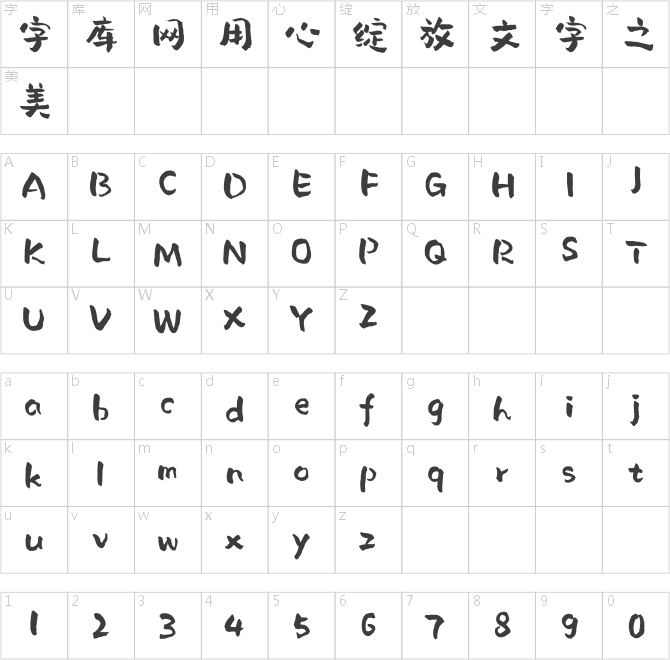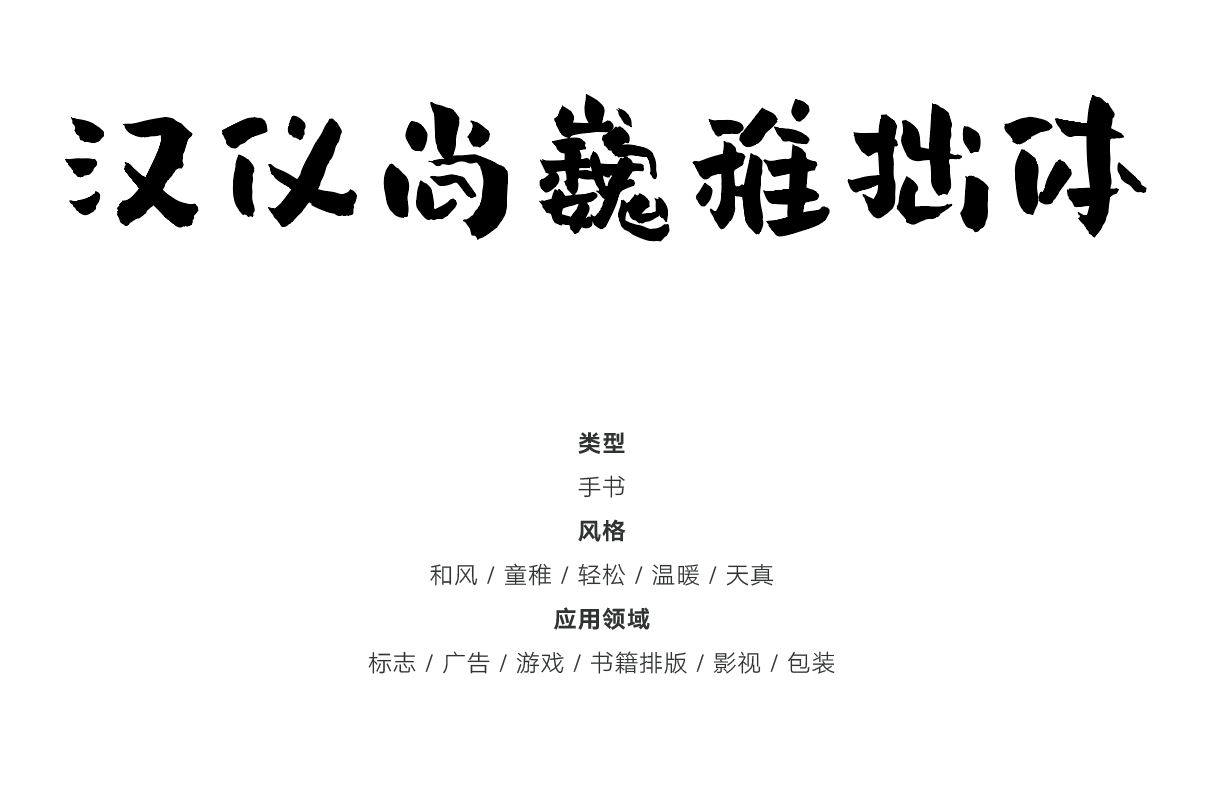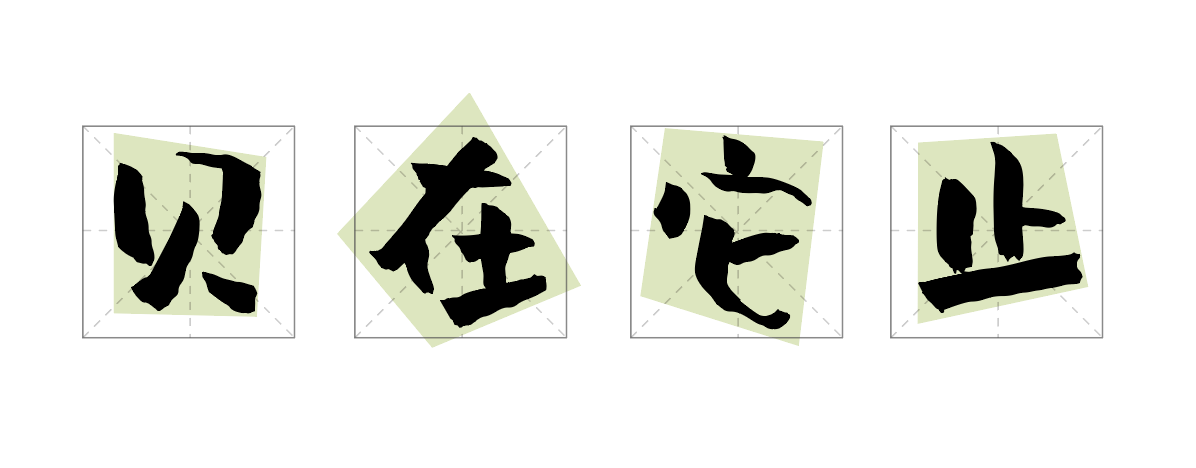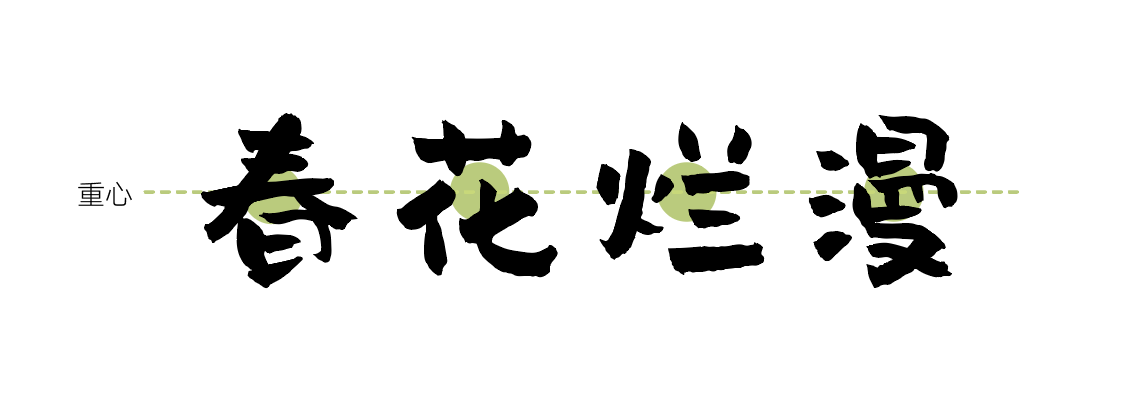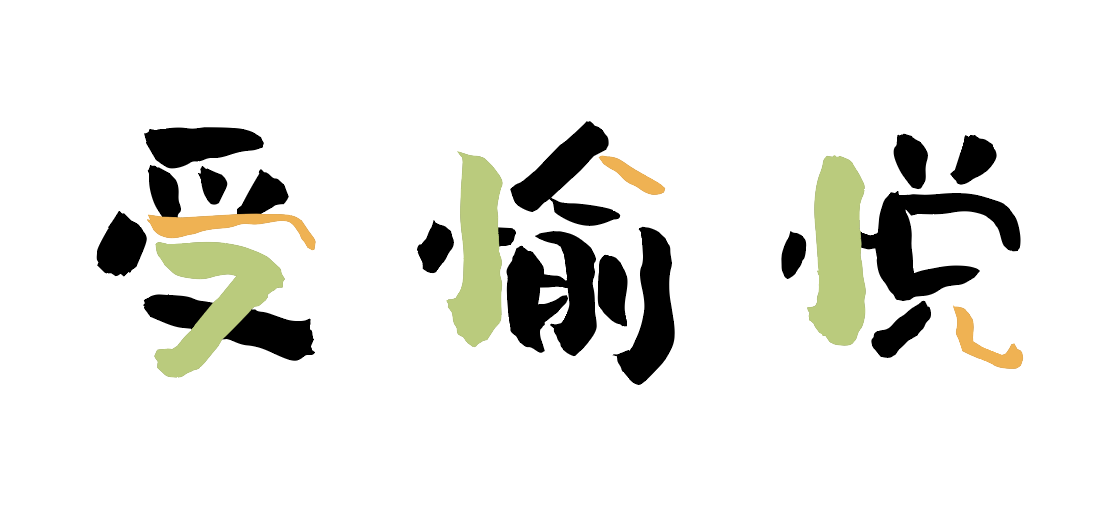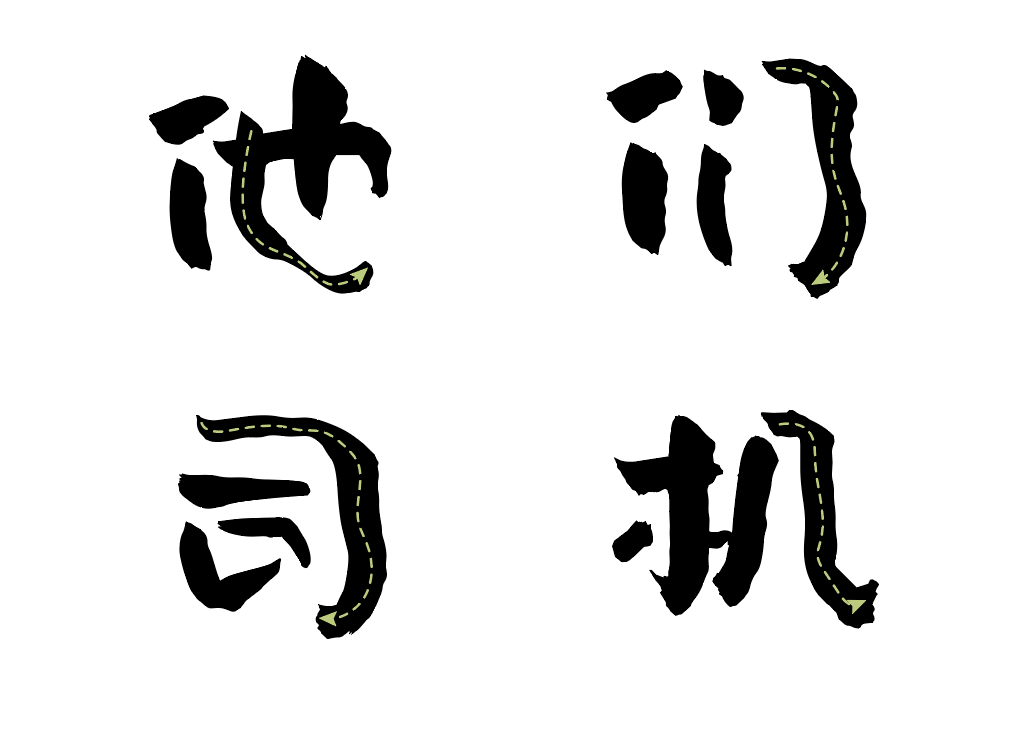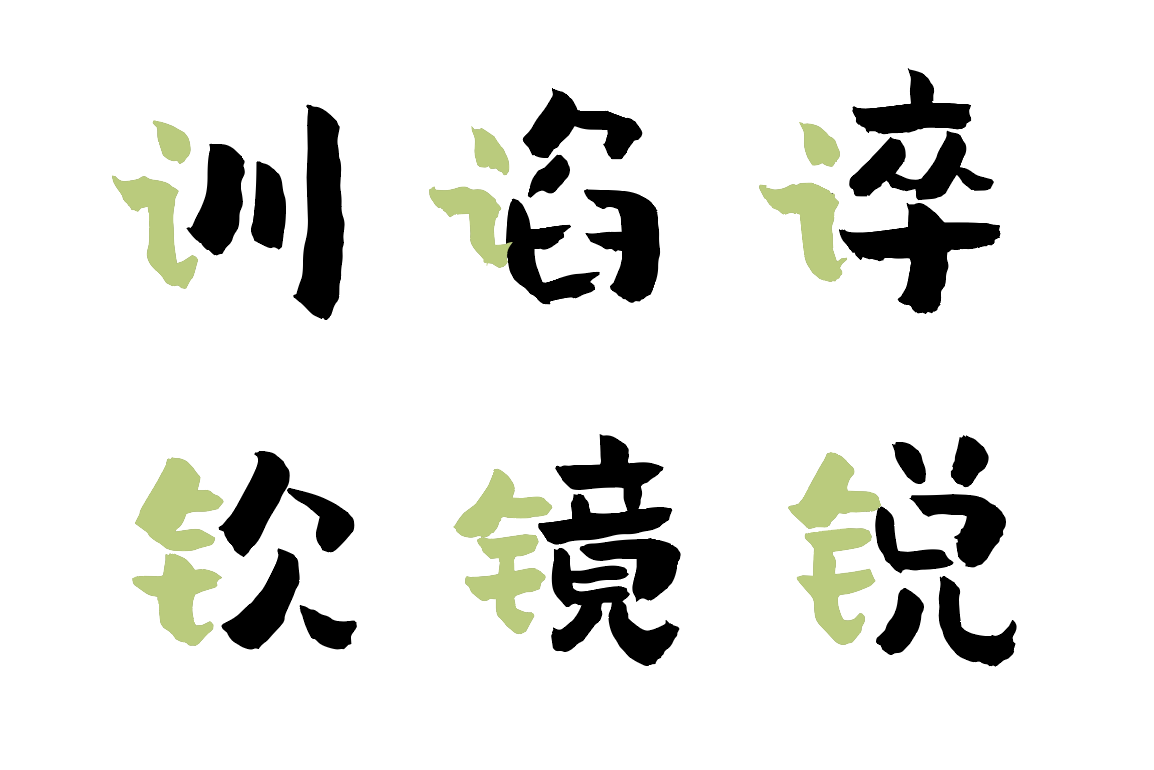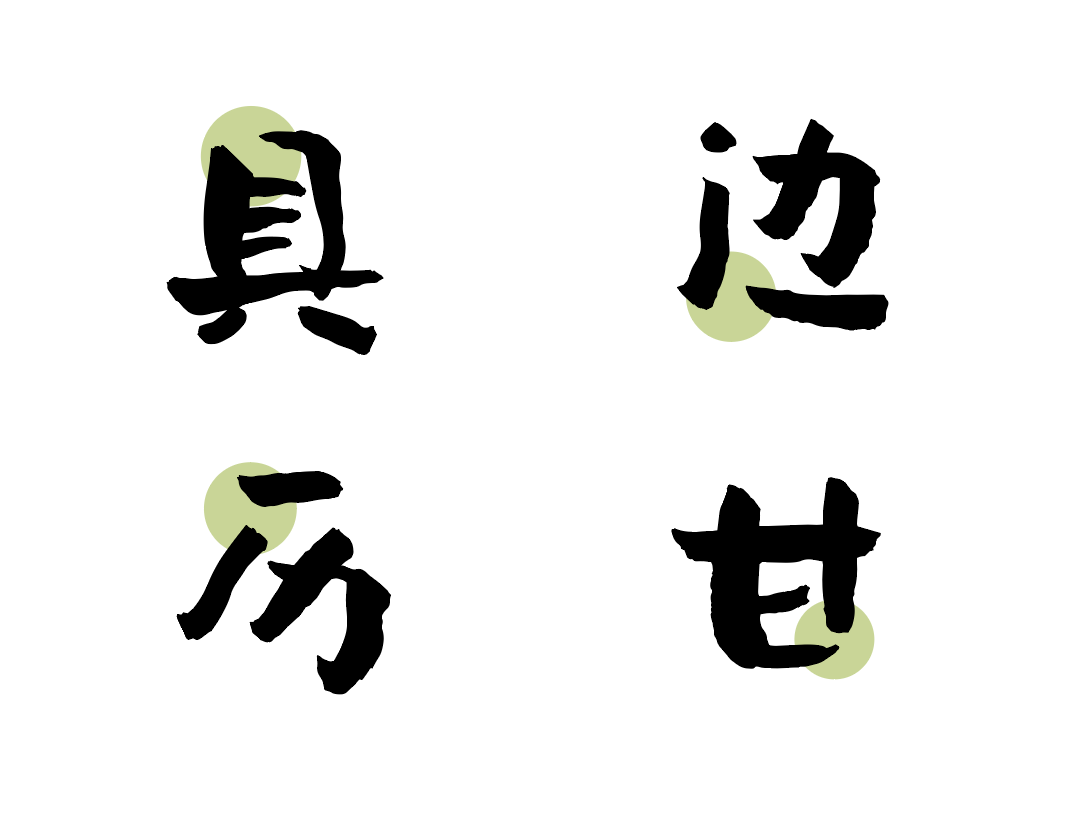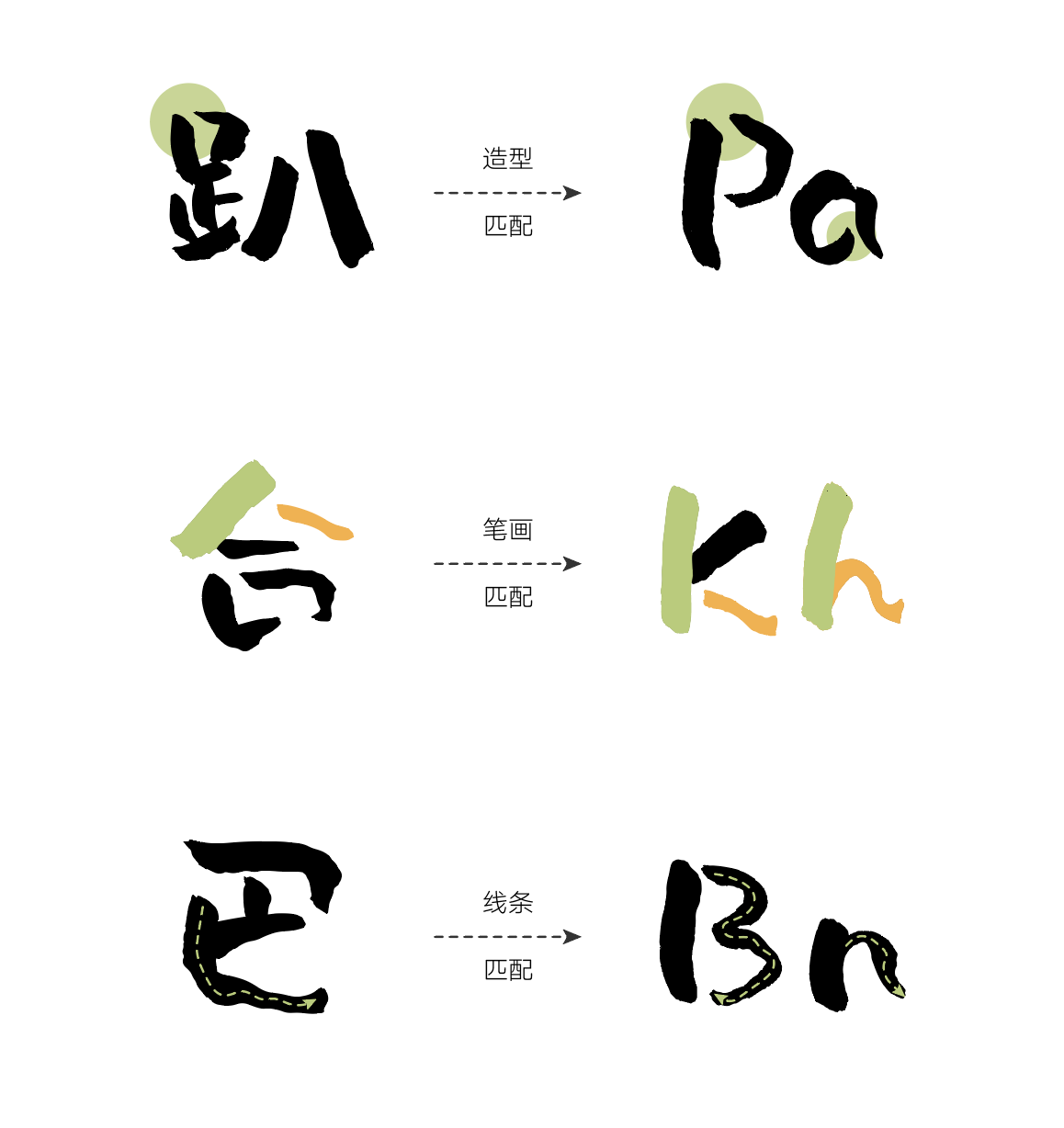
漢儀尚巍稚拙體 | 天真稚拙
漢儀尚巍稚拙體為90后新銳字體設計師尚巍所做的一款有著日和風格的手書字體。作者在書寫時處于非常放松的狀態,使得字體給人一種輕松緩和的視覺效果,非常具有親和力。
漢儀尚巍稚拙體 | 字形多變
漢儀尚巍稚拙體的字形布局考究、張弛有度。筆畫排布看似隨意卻又能夠在視覺上保持統一,給人帶來溫暖的松弛感和親切感。
漢儀尚巍稚拙體的結構多變,部分字形打破常規。雖然看似放縱隨意,但其實每個字都被限制在字框中。
漢儀尚巍稚拙體 | 筆畫童稚
漢儀尚巍稚拙體筆畫的粗細變化十分明顯,作者用筆時而堅實有力,時而頑皮隨性。
漢儀尚巍稚拙體的書寫手法質樸拙嫩、直率自然,筆畫提按過渡明顯,線條變化自由生動,看似如兒童書寫般彎曲隨意卻又帶一股力度和韌勁。
漢儀尚巍稚拙體在筆畫銜接處的留白讓人聯想到兒童在寫字時的笨拙可愛,生命力表現十足。
漢儀尚巍稚拙體保留手寫的獨創性,減少機械復制,使相同的偏旁出現不同的手寫效果。
中西文匹配
漢儀尚巍稚拙體的西文充分吸收了中文筆畫造型和線條的特點,形成了帶有樸拙韻味、風格童稚天真的字母。中西文搭配使用時和諧統一。
排版效果